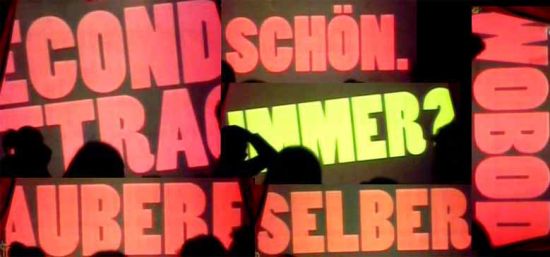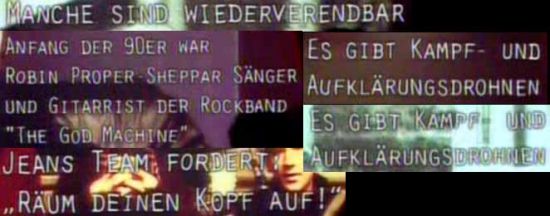
Suche zwei Schriften aus »Sendung ohne Namen« (ORF)
Die ORF-»Sendung ohne Namen« hat ein recht eigenwilliges Aussehen und Konzept. Vielleicht kennt sie der ein oder andere? Ich suche die in der Sendung verwendeten Schriften und konnte mittels »Identify a font« nichts finden. Deshalb belästige ich mal wieder dieses Forum. :wink:
Die Standardschrift (Ist in der Sendung immer in Bewegung, d.h. sie »zittert« und macht eine Art Wellenbewegung. Deshalb ist sie in den Bildern so verzerrt.):
Zweite Schrift: